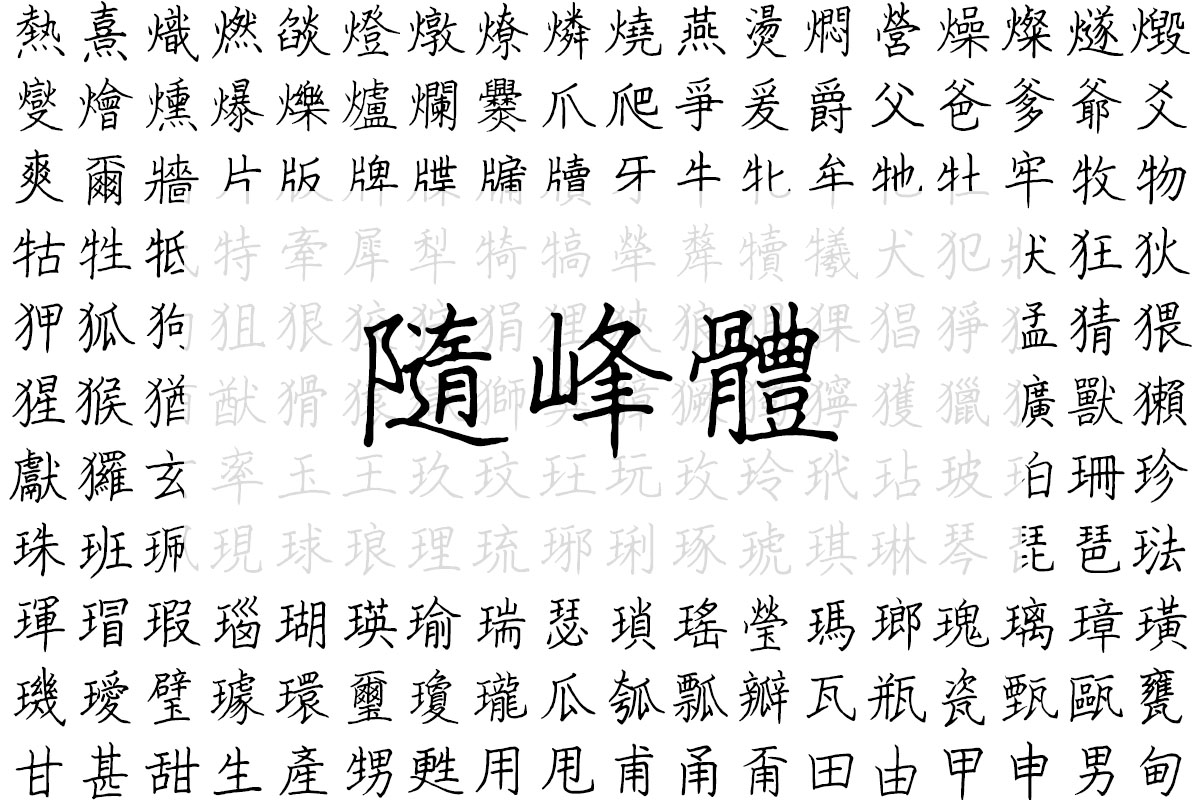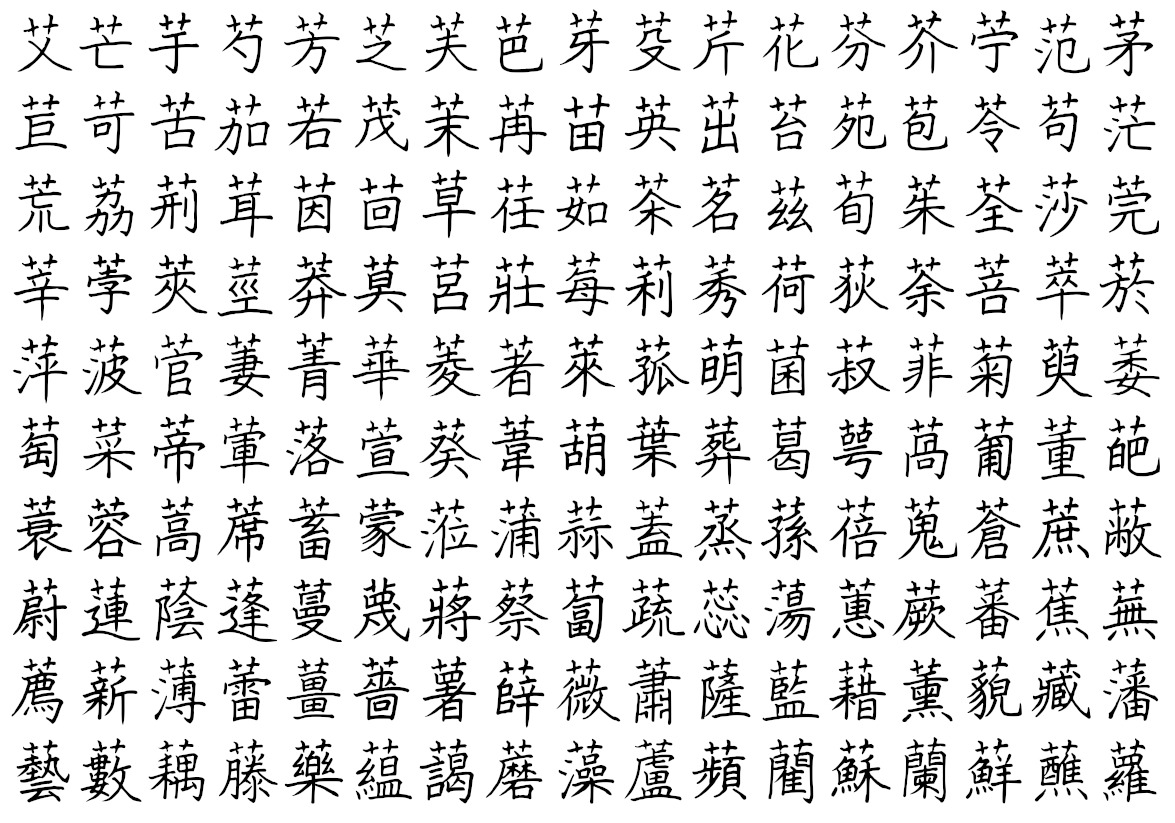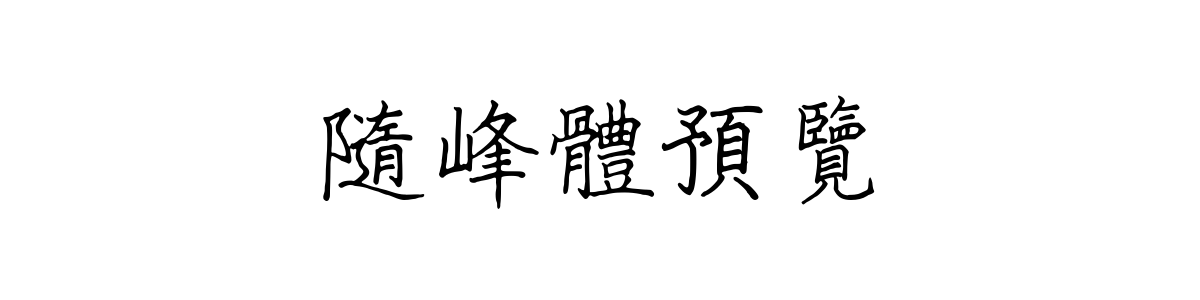
随峰体
随峰体(The Peak Font)是一款由香港创作者阿坤以啫喱笔逐字手写而成,是一款刻意保留书写痕迹与瑕疵的免费开源中文字体。该字体是创作者历时两年,用啫喱笔一字一字亲手书写后数字化完成的成果。其核心理念在于保留最原始、真实的手写质感,不刻意修整笔画的不均匀、墨迹渗透或微小的颤抖等“瑕疵”,以此传递手写的温度与个性。
字体风格
随峰体的风格核心是“真挚且不完美的生活笔迹”。它完全摒弃了工业字库的整齐划一,最大化地还原了日常用啫喱笔在纸上书写的真实状态:笔画粗细随书写力度自然变化,转折处带有圆润的钝感,起笔收笔的痕迹清晰可见,甚至保留了因书写速度产生的飞白和轻微的抖动。
这种“不完美”恰恰是其灵魂所在,赋予字体强烈的生命感、人情味和即兴书写的随意性。它不像书法字体那般追求艺术性,而是更贴近普通人笔记、日记或随手便条中的字迹,散发出亲切、质朴、毫无距离感的视觉气质,仿佛能透过屏幕闻到纸墨的香气。